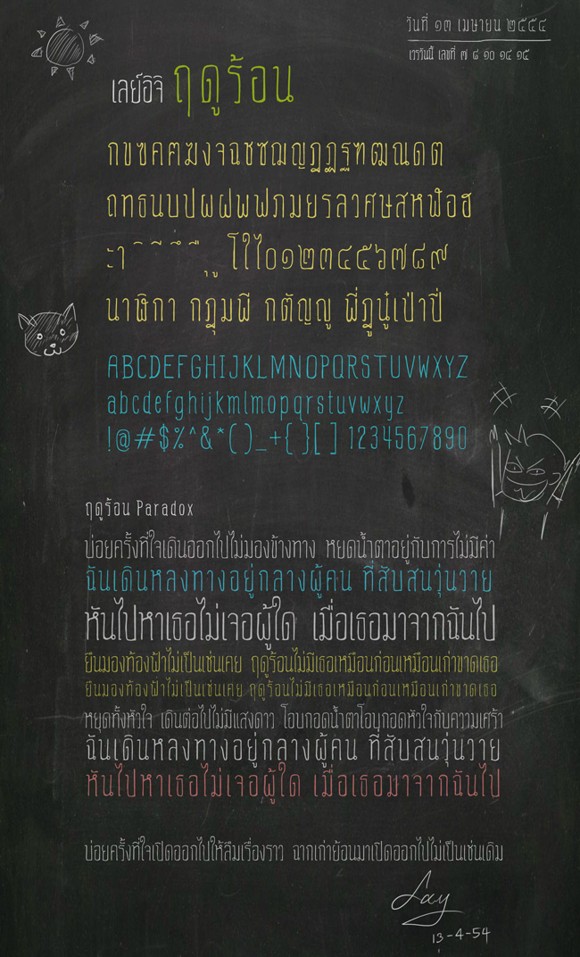
Layiji ฤดูร้อน
ฟอนต์.คอม ขอเสนอฟอนต์ใหม่จากคุณเลย์อิจิเจ้าเก่าด้วยความยินดียิ่งครับ คุณเลย์อิจิแกเป็นคนทำฟอนต์ชนิดที่พวกเราเรียกกันว่าเป็นนัก “มวยไม่มีค่าย” (อย่าผวนสิ) คือทำฟอนต์ด้วยความสนุกและไม่มีกฎเกณฑ์มาครอบงำ (เอ๊ะตกลงมันดีไม่ดี) ทำให้ได้ฟอนต์ที่แปลกแหวกแนวหลากหลายทยอยมาอวดพวกเราอยู่บ่อยๆ เอ้า เชิญชมและดาวน์โหลดได้เลยครับ
อยู่ๆ ผมก็อยากได้ฟอนต์แนวตีบๆ ลีบๆ ขึ้นมา อาจจะมาจากการเห็นฟอนต์ฝรั่งสวยๆ บางตัวล่ะมั้ง
เลยทดลองทำดูตัวสองตัว … เออ เข้าท่าแฮะ ท่าทางฟอนต์นี้จะเป็นประโยชน์กับงานนิตยสาร
หรือหนังสือวรรณกรรม รวมไปถึงงานดีไซน์รุ่นใหม่ๆ พอสมควร เลยทำออกมาภายใต้ชื่อซี่รี่ส์ว่า
ซึ่งในตัวฟอนต์นี้จะประกอบไปด้วย
1. เลย์อิจิ ฤดูร้อน (ธรรมดา)
เป็นฟอนต์ตีบๆ บางๆ ช่องไฟชิดๆ ซูเปอร์สลิม
2. เลย์อิจิ ฤดูร้อน มาก
คือตัว Bold ของฤดูร้อน ช่องไฟก็ชิดๆ เหมือนเดิม แต่เพิ่มความหนาขึ้นซึมซับได้มากขึ้น
3. เลย์อิจิ ฤดูร้อน ยาว
คือฟอนต์ที่ผ่านการขยายช่องใฟให้กว้างขึ้นเหมือนมีปีก สบายตัวไม่หวั่นแม้วันมามาก
4. เลย์อิจิ ฤดูร้อน ยาวมาก
ตัวนี้ทั้งกว้างทั้งหนา รองรับทุกอารมณ์สบายทุกท่วงท่าแม้ในขณะหลับ